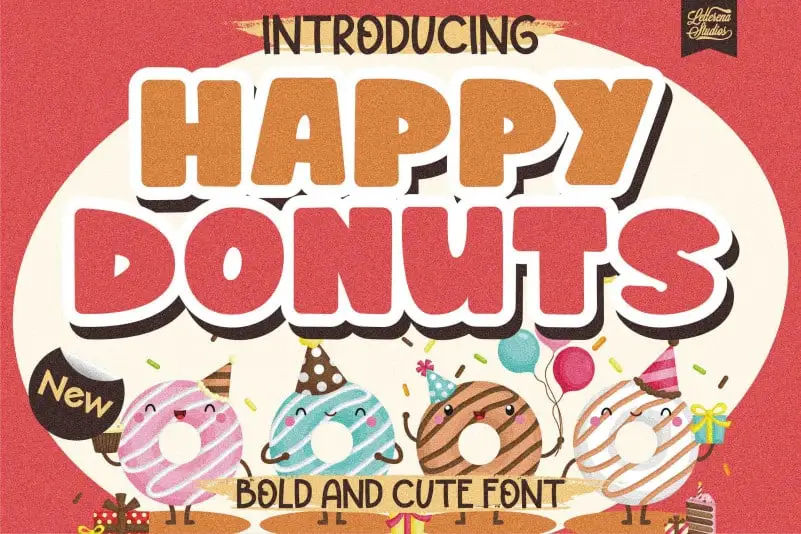
Happy Donuts Display Font – Fonte Grátis
Happy Donuts Display Font
A fonte Happy Donuts Display é uma escolha perfeita para aqueles que buscam um visual alegre e divertido. Com letras grossas e cheias de personalidade, essa fonte é ideal tanto para projetos digitais quanto para o papel. Suas letras alegres são perfeitas para criar identidades visuais memoráveis, como logotipos, selos ou embalagens de produto, trazendo um toque de diversão e criatividade sem perder a qualidade. Suas características fun e divertidas fazem dela uma escolha ideal não apenas para homewares, mugs, cartões personalizados, camisetas ou livros, mas também para qualquer projeto que precise de um arco de beleza e peculiaridade na tipografia. Adaptable e versátil, a fonte Happy Donuts Display é a companheira perfeita para quem busca uma estética única em seus projetos gráficos.